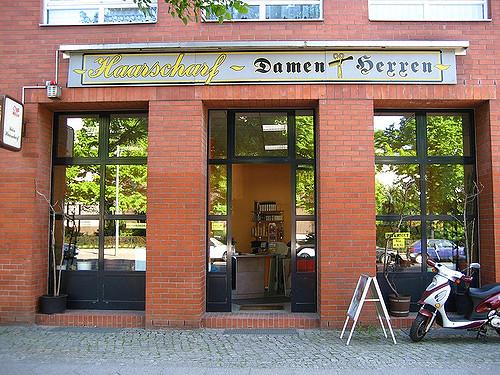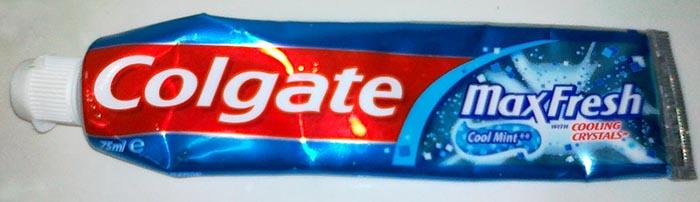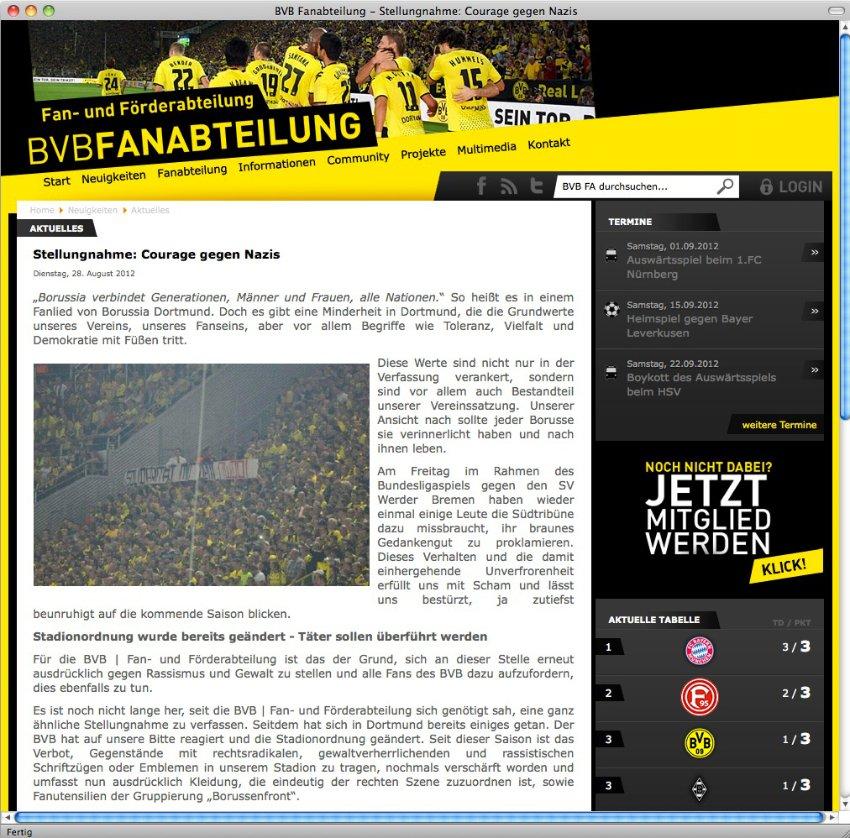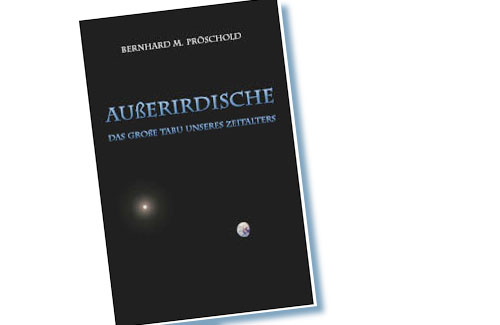
Vielleicht wurden ja Mehrfachnennungen berücksichtigt, z.B. bei Antworten wie: »Spontan würde ich sagen: beide Länder gleichermaßen. Aber wenn ich ehrlich bin, muss ich sagen: eher … . Obwohl, wenn ich mir die Reaktionen meiner Mitbürger sowohl hier als auch dort anschaue, läuft es am Ende vielleicht doch auf keins von beiden hinaus.« ;-)
Heimat ist vielschichtig und dynamisch. Nach meinen Erfahrungen wollen die wenigsten multikulturellen Menschen in nur eine Schublade gesteckt werden. (Das betrifft übrigens nicht nur Deutsche mit türkischen oder anderen »südländischen« Vorfahren. Bei Menschen, die/deren (Groß-)Eltern seit über 60 Jahren westlich von Oder und Neiße leben, sich aber immer noch als Schlesier oder Ostpreußen verstehen, ist das nicht anders.)
Vielleicht wurden ja Mehrfachnennungen berücksichtigt
Dann sollte man keine Tortengrafik verwenden (eine Torte ist geschlossen und kann nicht mehr als 100 Prozent fassen), sondern Balken.
Diese Torte hat deutlich mehr als 100%, wenn dieser kleine Schnipsel schon 45% sind :-P
Real-Satire aus dem Hamburger Abendblatt:
»Eine 51 Jahre alte Lehrerin unterrichtete Deutsch in einer sogenannten
Vorbereitungsklasse, in der Migrantenkinder die deutsche
Sprache lernen, das für den späteren gemeinsamen Unterricht notwendig ist.«
Real-Satire aus dem Hamburger Abendblatt:
Demnach: «… aus der Hamburger Abendblatt:».
Wir brauchen ein Versal-Esszett, wie dieses Buchcover beweist:
Wieso? Diese Lösung verrät mir doch mit einer einfachen typografischen MaBnahme, dass wo Ramsch drauf ist der womöglich auch drin ist.
Für den Fall, dass der Umschlag selbst gestrickt und nicht von einem Profi gestaltet worden ist: Nicht jeder kennt die Regel, wonach ß im Versalsatz durch SS ersetzt wird (und wer die nicht kennt, wird vermutlich vom Versal-ß noch weniger wissen).
Nachhaltig wird das Problem wohl erst gelöst sein, wenn
• Tastaturen verbreitet sind, mit denen sich ẞ per ⇧-ß erzeugen lässt und
• toUpper(ß) überall und verlässlich ẞ erzeugt.
Aber das wird noch eine Weile lang Zukunftsmusik bleiben, so dass wir auf absehbare Zeit mit verschiedenen Notlösungen und daraus resultierenden Anwenderfehlern leben müssen.
Siehe letzte zwei Absätze.
Die Bildunterschrift im Spiegel-Online-Artikel beginnt mit »BVB-Fanabteilung«, aber das ist natürlich falsch. Tatsächlich handelt es sich um die BVB | Fan- und Förderabteilung!
Man sieht: was 15 Jahre lang nur lesezeichenoptimierter Webseitentitel sein durfte, hat es mittlerweile in den Fließtext und evtl. gar zur echten Wortmarke geschafft!
Ich finde es ja ohnehin schon etwas schräg, wenn man ausgerechnet eine Zahnpasta nach einem Schweizer Schriftsteller benennt, aber warum anglisiert man seinen Namen dann auch noch künstlich? Wo soll das noch hinführen, was kommt als nächstes? Eine Schuhcreme Friedrich Whither"n"faint?
Oder auch … :-)
Durch das oben nach rechts abgebogene t tendiert das in dem Falle ja fast schon zu einer korrekten Ligatur aus ſ und z mit Unterlänge ...
... wenn da nicht das untere Ende des t wäre ...
Nett auch die Antwort bei twitter auf den flasch mit e geschriebenen Apo-Shake:
... für normal- und rothaarige Damen ;-)
Mist, da war wer shcneller ;-)